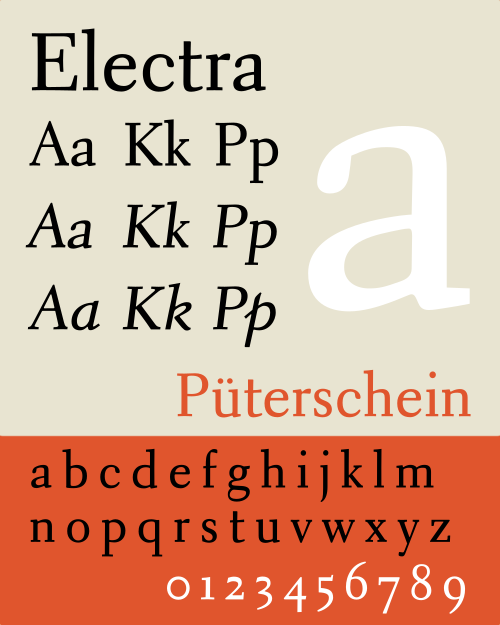
| カテゴリ | セリフ |
| 分類 | 移行期 |
| デザイナー | WA ドウィギンズ |
| 鋳造所 | ライノタイプ |
| リリース日 | 1935年 (ローマ字/斜体) 1940年 (筆記体) |
| バリエーション | エレクトリック アズザ パーキンソン エレクトラ ポエッツ エレクトラ LfA アルミニア (写真) |
| 別名 | エランテ トランジショナル 521 |
エレクトラはウィリアム・アディソン・ドウィギンズがデザインし、 1935年以降マーゲンターラー・ライノタイプ社が発行したセリフ書体である。本文用に作られた書体で、ドウィギンズはこのデザインを「個性」のある「現代的なローマン体」にすることを意図したものと説明し、歴史的なモデルを直接復活させることは避けた。そのため彼は「旋盤から出てくる金属の削りくずのように」電気と鮮明な現代性を連想させるエレクトラという名前を選んだ。[1] [2] [3]
ゆっくりとした発展を経て、エレクトラは金属活字時代後期のアメリカ印刷業界で人気の書籍用書体となった。[4]デザインが現代の印刷技術にうまく適合しなかったこともあり、人気が衰えた後、何度か復活版がリリースされた。
レタリングアーティストとブックデザイナーとしてのキャリアを確立した後、ドウィギンズは1929年にマーゲンターラー・ライノタイプ社にコンサルタントとして雇われ、書体デザイン責任者のショーンシー・H・グリフィスとパートナーシップを築きました。グリフィスはドウィギンズの残りのキャリアを通じて彼のすべての書体の制作を管理することになります。[5]ドウィギンズの最初の書体はメトロで、流行していた FuturaやGill Sansなどの新しいヨーロッパの書体への回答として意図されたサンセリフでした。
メトロの後、ドウィギンズは長文の読み物に適したセリフ体の書体デザインに着手した。彼が表明した意図は、ルネッサンス期の書体デザインを模倣した、ほとんどの当時の書体で見られる歴史的復興のアプローチを避けることだった。ドウィギンズはこのデザインを風変わりなパンフレット『エンブレムとエレクトラ』で宣伝し、その中でこのデザインは書家および教育者として有名な日本の僧侶、弘法大師の精神と交信した結果生まれたものだと主張した。 [1] [6] ヴィンセント・コナールは、エレクトラの細いモノラインのセリフが18世紀のピエール=シモン・フルニエの書体にいくらか似ていると示唆しており、このためエレクトラは一般に「過渡期」に分類されている。[7] 「Q」のスワッシュテールもジョン・バスカヴィルの書体を彷彿とさせる。
金属製のエレクトラには、文字の数字と2種類の長さのディセンダが用意されており、2つのうち長い方(ドウィギンズが好んだ)にはリーディングが必要でしたが、短い方は固定できました。[3]
Electra の最初のリリースにはイタリック体は含まれておらず、代わりに Dwiggins は手書きの特徴を一切持たずに文字を斜めにした斜体を提案した。これは明らかに、筆記体のイタリック体よりも適切な二次書体としてこのアイデアを推進したStanley Morisonの主張に影響されたものだった。しかしこれは人気が出ず、Dwiggins は「Electra Cursive」と名付けた真のイタリック体をデザインし、1940 年にリリースされた。 [4]この時点から、Electra はアメリカの印刷業界で人気の書籍書体となった。Walter Tracy はこれをアメリカの書籍の「現代の古典」と表現したが、書体デザインとして最初に発表された Dwiggins のイタリック体は一部の文字のバランスが不自然だと感じていた。[4]イギリスでは戦争により Electra Cursive がリリースされず、この書体はかつてほどの人気を得ることはなかった。[3]
デジタルによる復活と解釈
Electra は 1994 年に Alex Kaczun によってLinotypeとAdobe向けにデジタル化されました。標準版とディスプレイ版の両方が通常版と太字で作成されましたが、標準版でも一般的な文字サイズでは細く見えます (金属活字の初期のデジタル化でよく見られる問題)。このバージョンでは金属活字の長いディセンダーが使用されています。イタリック体は Electra Cursive です。大部分は金属活字のアウトラインの正確なコピーですが、小文字の「f」には Linotype マシンの制限がなく、長いオーバーハングが与えられています。Linotype リリースではスモール キャップスとテキスト数字に別々のフォントが使用されていますが、Adobe リリースではこれらがOpenType機能として組み込まれています。[8] [9]
ビットストリームはエレクトラをトランジショナル521としてデジタル化した。これはデジタル製品の中で最も基本的なもので、基本的なラテン文字セットといくつかのタイポグラフィック機能のみを備えている。[10]イタリック体はエレクトラ筆記体を使用しており、通常のウェイトでのみ利用できる。ティルデがリリースしたこのデザインのバージョンには、アクセント付き文字と特殊文字の範囲が広くなっているが、追加のウェイトや機能はない。
CompugraphicのコールドタイプElectra コピーであるElanteは、Monotype からデジタルで入手できます。このコピーは、Electra の金属バージョンよりも短いディセンダーを使用しています。
Jim Parkinson は、オリジナルの Electra に基づいていくつかのフォントを作成しました。
- 1990年代初頭のサンフランシスコ・クロニクルの社内書体で、エレクトラとして知られるようになった。エレクトラよりも太く、エクステンダーが短かった。[11]パーキンソンは、見出し用に、ドウィギンズのサンセリフ体メトロをデジタル化して補完した。[12]
- Azuza(2001)[13]は、Electricの全体的な比率を維持しながら、より洗練されたディテールを追加しました。ライト、ミディアム、ボールドの3つのウェイトで制作され、イタリック体はElectra Cursiveに基づいています。
- パーキンソンエレクトラ(2010年)は、ライノタイプ社がオリジナルのデジタル版を改良して制作したものです。1992年版よりも自由な解釈で、より太いレギュラーウェイトとより繊細なセリフが特徴で、ページ上での存在感を高めています。レギュラー、ボールド、ヘビーの3種類のウェイトで制作され、すべてエレクトラ筆記体に基づいたイタリック体です。[14]
- アルミニア(2017年)、ドウィギンズのオリジナルのデザイン画からデジタル化されたもので、オリジナルの斜体と後の筆記体の両方でイタリック体になっています。最初の金属バージョンを反映し、太字はありません。これは、回顧展「WAドウィギンズ:デザインにおける人生」で使用するためにレターフォームアーカイブのために特別に作成されたもので、本の設定に必要な基本的な文字セットのみを含む進行中のバージョンがクラウドファンディングの支援者に配布されました。ただし、完成次第、限定的に商業的にリリースする予定です。[15]
Poets Electraは、アメリカ詩人アカデミーのためにコマーシャル・タイプ社のクリスチャン・シュワルツとミゲル・レイエスがデジタル化したカスタム版である。[16]彼らは、ワールド・ワイド・ウェブで使用するフォントというプロジェクトの要件に応えて、8ポイントの金属活字のElectraを使用することを選択した。非常に小さな印刷サイズに対応する物理的な活字は、画面上の文字サイズに対応するデジタルフォントのそれと似ている。[17]アカデミーの公式印刷物で使用するために、 やや太めのバージョンであるPoets Electra No. 2も制作された。
サイラス ハイスミスは、ドウィギンズの作品に触発されて、いくつかの新書体をデザインしました。これらのうち、Prensa (1999、エルサルバドルのLa Prensa Gráfica用) は、Electra の影響を最も直接的に受けています。Prensa は、Electra のオリジナルの斜体を彷彿とさせる、特に抑制されたイタリック体で、手書きよりもローマン体に近い筆記体の文字を使用しています。
- エリック・ギルによるジョアンナはエレクトラと同時期にデザインされたもので、「人間性」と「現代性」のバランスをとった本の書体を作ろうという同じ衝動から生まれたもので、同様に抑制されたイタリック体である。
- ヤン・ファン・クリムペンによる Romulus は、傾斜したローマン「イタリック」を備えた 1930 年代の別のブックセリフ書体です。(別のチャンセリーイタリックであるCancelleresca Bastarda は同じシリーズの一部ですが、アセンダとディセンダがはるかに長いため、コンパニオンイタリックとして使用できませんでした。)
- 『エレクトラ』の宣伝用パンフレット『エンブレムズ・アンド・エレクトラ』のイラスト。この絵はもともと『サタデー・レビュー・オブ・リテラチャー』のために描かれたものですが、ドウィギンズの作品の雰囲気を伝えるために見本として再掲載されました。